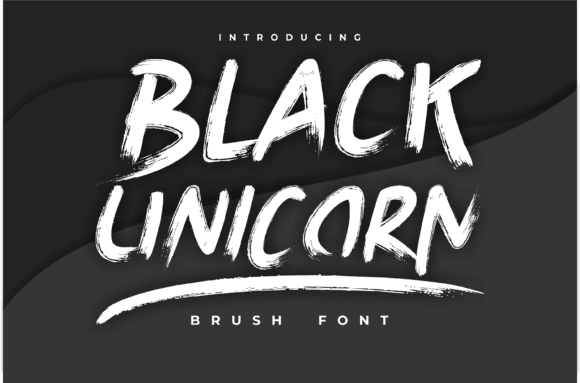
Название: Black Unicorn Font
Черный Единорог - это рукописный шрифт в стиле кисти.
Этот шрифт имеет много альтернативных лигатур и слешей, чтобы он действительно выглядел как ваш собственный почерк. Легко поднимайте слеши, просто напечатайте несколько раз символ подчёркивания. Идеально подходит для ваших творческих проектов в этом сезоне.